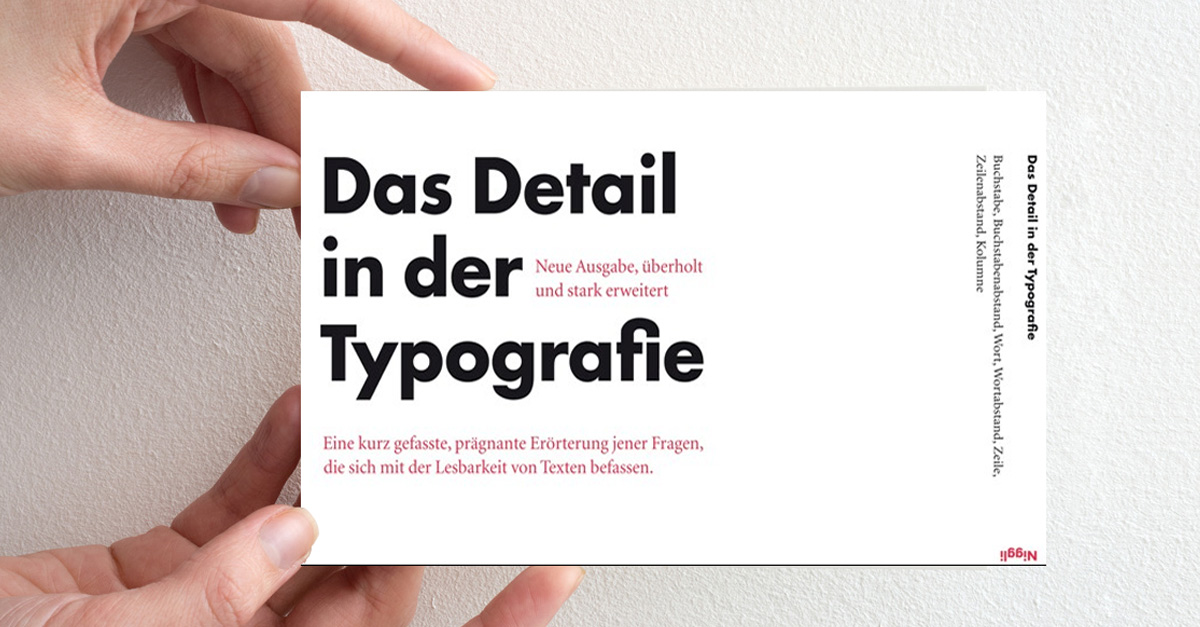
Fachbuch zum Thema Typografie
Das Taschenbuch des Schweizer Gebrauchs- und Industrie-Grafikers Jost Hochuli erschien erstmals im Jahr 1987 in einem Verlag namens Compugraphic in den USA. Es scheint fast so, als hätte man damals schon geahnt, dass die Digitalisierung in den folgenden Jahrzehnten großen Einfluss auf die Rezeption von Inhalten nehmen würde. Doch selbst in der aktuellen 2., überarbeiteten Ausgabe spielt die Digitalisierung keine exponierte Rolle. Die Betrachtungen zum Thema Schrift bleiben unabhängig vom Trägermedium und machen das Büchlein zu einem universellen Werk, mit dem man sich in kurzer Zeit über Wesentliches in der Typografie informieren kann.
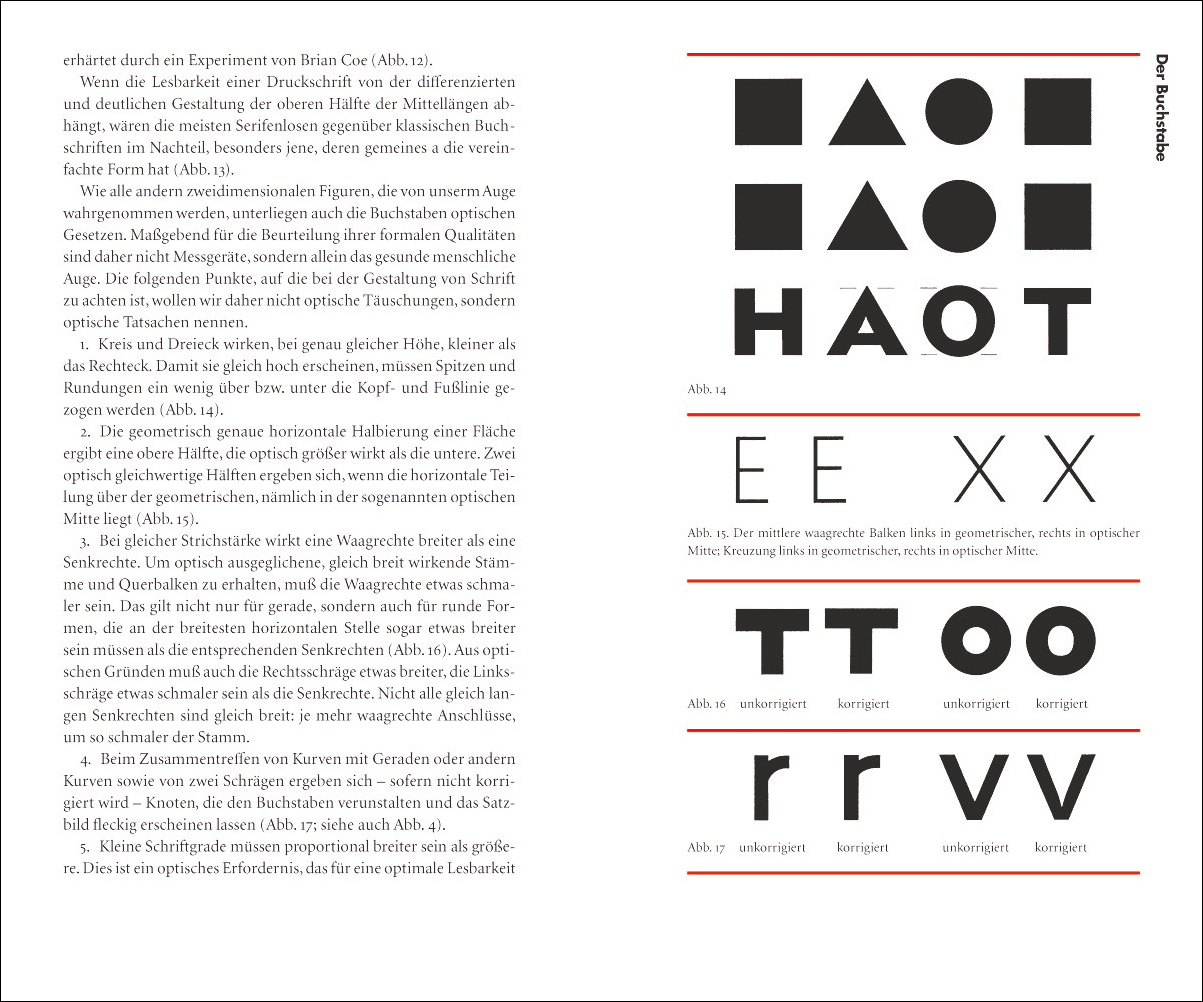
Mit Liebe zum Detail
Im Mittelpunkt stehen die Mikro- und Detailtypografie. Es geht um die Feinheiten der Schrift, um Buchstaben, den Buchstabenabstand, das Wort und den Abstand zwischen einzelnen Worten, um die Zeile und den Zeilenabstand und schließlich um die Kolumne.
Hochuli erläutert vorneweg den Lesevorgang, bei dem unsere Augen in kurzen Bewegungen (Saccaden) von Wort zu Wort springen. Schriften für den Mengensatz sollen den Lesevorgang unterstützen und das Auge nicht durch dekorative Elemente „aufhalten“ oder wie er es der Autor treffend beschreibt: „Die Schrift drängt sich nicht zwischen Textinhalt und Leser.“
Sensibilisierung für Typografie
Hochuli sensibilisiert seine Leser dafür, wie sich die verschiedenen Ausprägungen von Schriften auf die Lesbarkeiten von Texten auswirken. Dieses Buch eignet sich daher für alle, die sich schon immer einmal grundsätzlich mit dem Thema Typografie beschäftigen wollten und Schriften nicht mehr länger „nach Gefühl“ und rein ästhetischem Empfinden aussuchen möchten. Mit seinen 68 Seiten ist es zwar recht dünn, allerdings braucht es etwas Zeit und Muße, um sich mit den Details zu beschäftigen. Denn ein großer Teil des Informationswertes steckt in den zahlreichen Abbildungen mit kleingedruckten Anmerkungen.